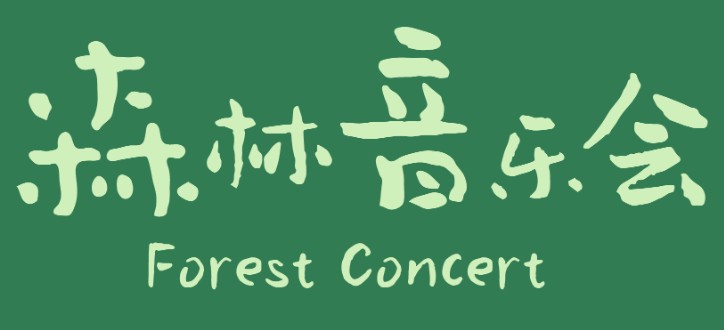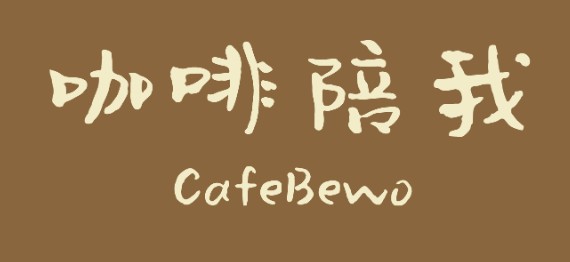
字体介绍:
2018年9月13日发售,喜鹊小轻松体,是使用小软笔,在7mm的格子上书写而成。几乎不施加多余的力,轻松地写一份滴滴点点的小字。表情幽默有点萌,给人一种,清爽不油腻的观感。
适用风格:
适用于排版可爱清新风格的正文或标题文字需求,如茶点轻食品牌,动漫创意、心情书写等。
符合GB 2312标准简体汉字,配有相应风格的英文以及标点。